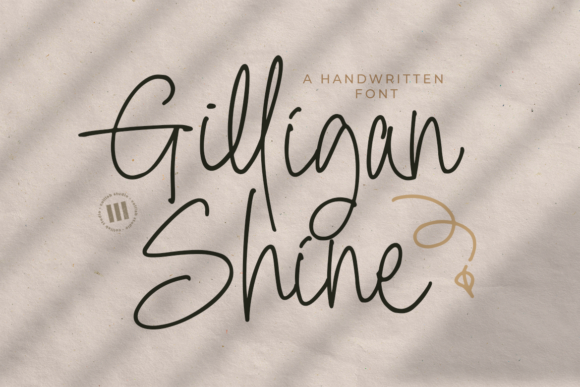
Gilligan Shine
Gilligan Shineのような高品質の素材をお探しの場合、このプレミアムパッケージはクリエイティブなプロジェクトに素晴らしい選択です。
POD(オンデマンド印刷)製品、結婚式の招待状、またはソーシャルメディアのグラフィックを作成している場合でも、Gilligan Shineは理想的です。